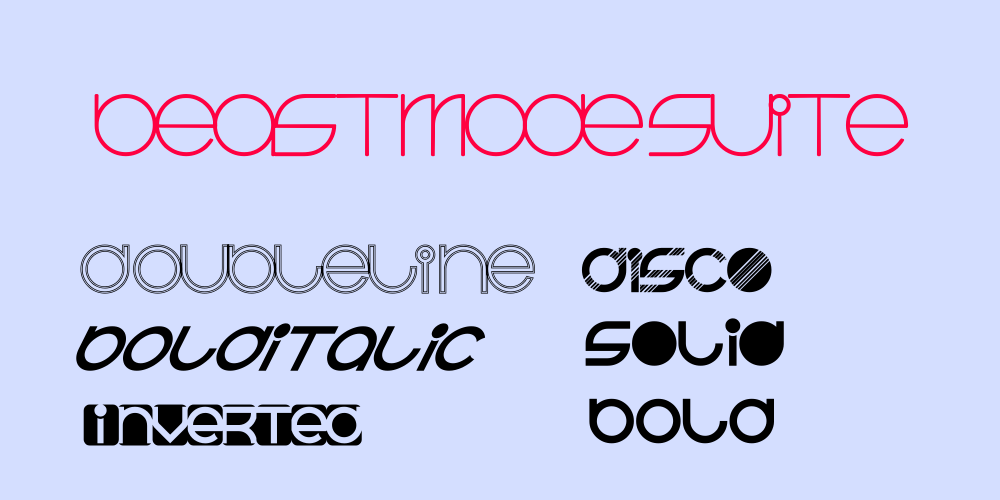
A ‘Beast Mode Suite’ é uma fonte Display cuidadosamente projetada pelo designer Hamilton para fornecer a sensação agressiva que você precisa para destacar seu design no ambiente competitivo do mercado de branding. Com um estilo robusto e uma paleta vibrante, esta família de fontes proporciona o tom perfeito para seus projetos visuais, seja em materiais de marketing ou criações digitais. Seu risco é grande: a ‘Beast Mode Suite’ combina linhas fortes e extremamente personalizadas com harmonia. Ela oferece uma ampla gama de opções, desde as tipografias mais leves até os traços mais robustos que vão transformar sua apresentação em algo realmente impactante. Este conjunto de fontes é perfeito para quem busca expressar vigor e força através de um design visual, criando uma identidade única e memorável. Para quem está sempre à frente da concorrência, a ‘Beast Mode Suite’ não apenas trará vida aos seus projetos visuais, mas também dará ao seu design o fator que impulsiona sua mensagem para além das bordas. A fonte oferece um conjunto completo de caracteres para suportar textos legíveis em qualquer situação, garantindo que a estética seja tão importante quanto a funcionalidade.